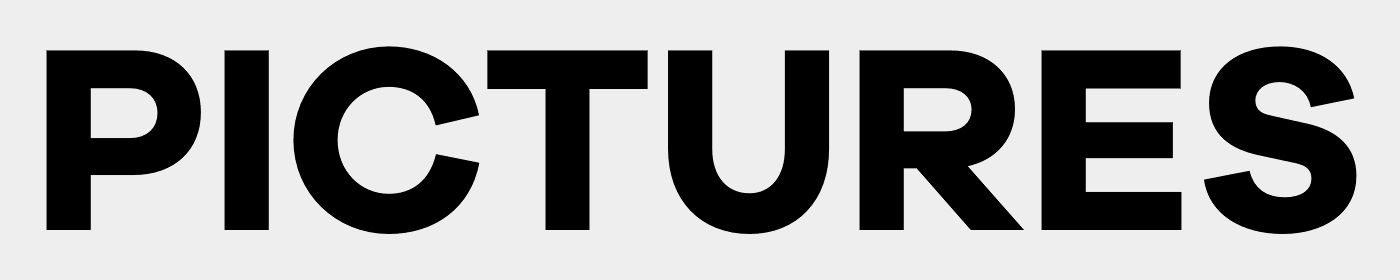
Suche Schrift von Digital Filmmaker Venom Pictures
Ich bin auf der suche nach dieser Schriftart von Venom Pictures die auf seinem Profilbild und Banner seines Facebooks accounts ist.
das ist eine von ganz ganz vielen klassischen groteskschriften (nur das sehr weit geschlossene »C« scheint etwas ungewöhnlich). lediglich die »E« sind durch waagrechte balken ersetzt (händisch).
kannst du selber in 5 min. nachbauen.
Dazu braucht es aber erst mal die pasende Schrift. Sehr verschlossenes C, R mit geradem Füßchen ... Das C findet man in mehreren Schriften, die ich bei mir in der Rubrik Grotesk -> Europa habe. Zwischen AG, Helvertica und Univers könnte sich da was rumtreiben?  (Anmerkung: Ich habe die traditionellen Grotesk in zwei Gruppen unterteilt: Europa und Amerika.)
Archivo von Omnibus Typ:
Das konnte eine ausreichend gute Basis für die Basteleien liefern? Nur das O gefällt mir irgendwie nicht ... Diese hier wäre etwas näher drann?
Typeface:	Forma DJR Text
Designer:	Aldo Novarese, David Jonathan Ross and Roger Black
Year:		1968, 2017
Publisher:	DJR
One of a set of Optical Sizes with the fonts Forma DJR Micro,
Forma DJR Deck, Forma DJR Display and Forma DJR Banner.